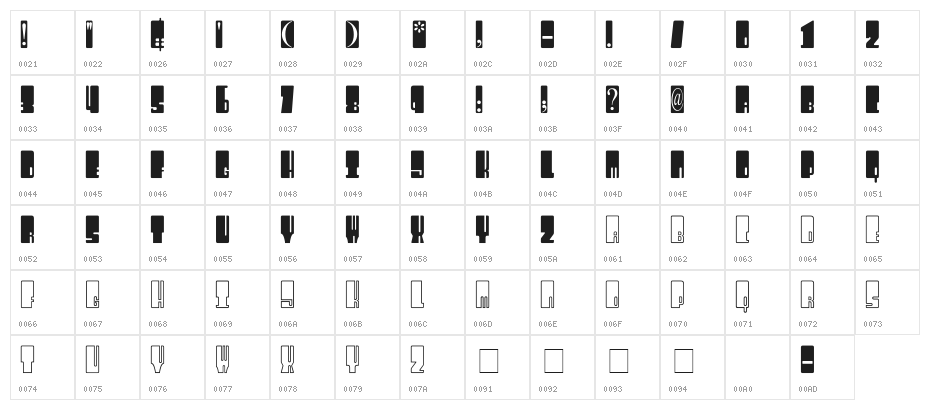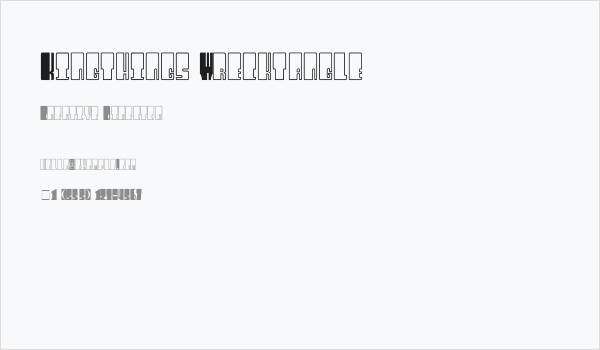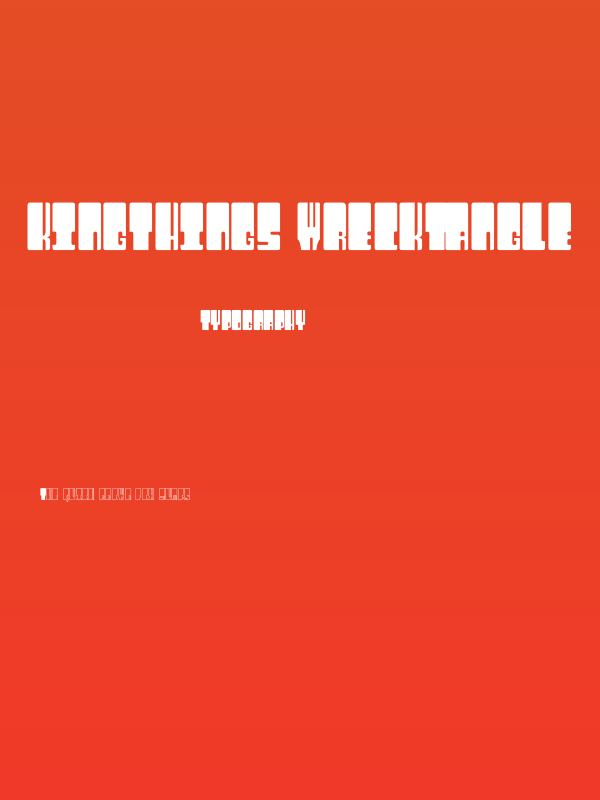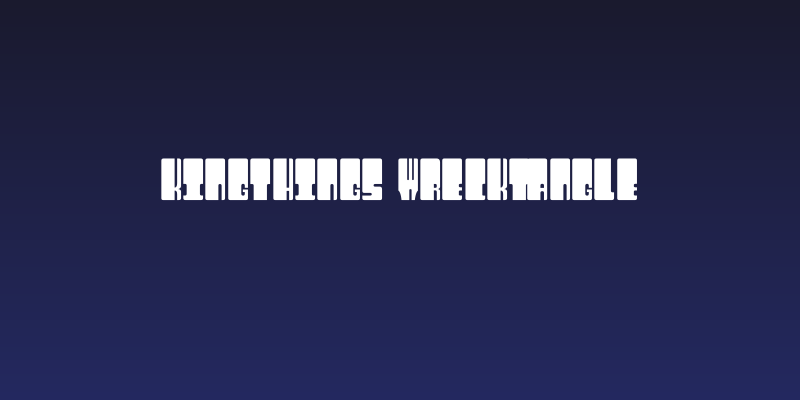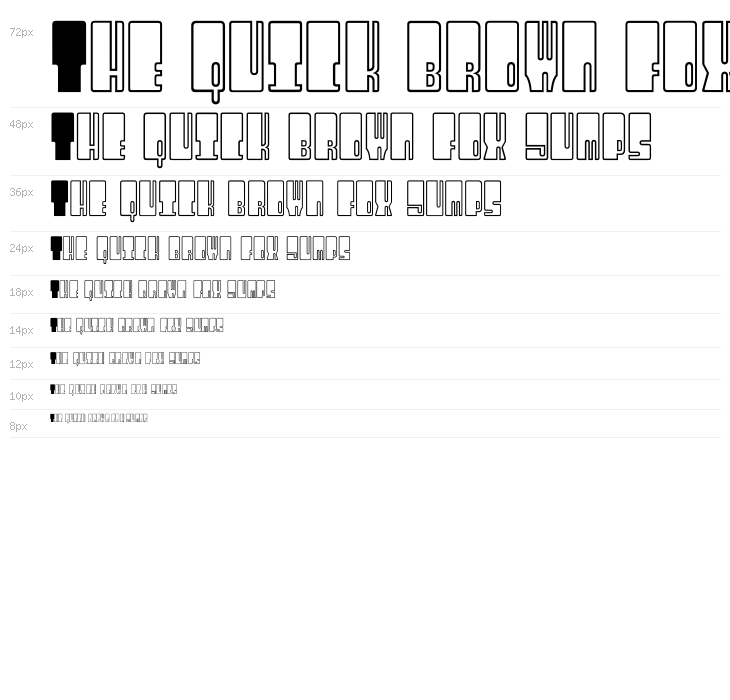
Kingthings Wrecktangle Font
| Stile generale | Modern, Retro |
| Progetti proposti | Ideal for posters, logos, and headlines where a bold and distinctive look is desired. Suitable for creative projects that require a playful and eye-catching design. |